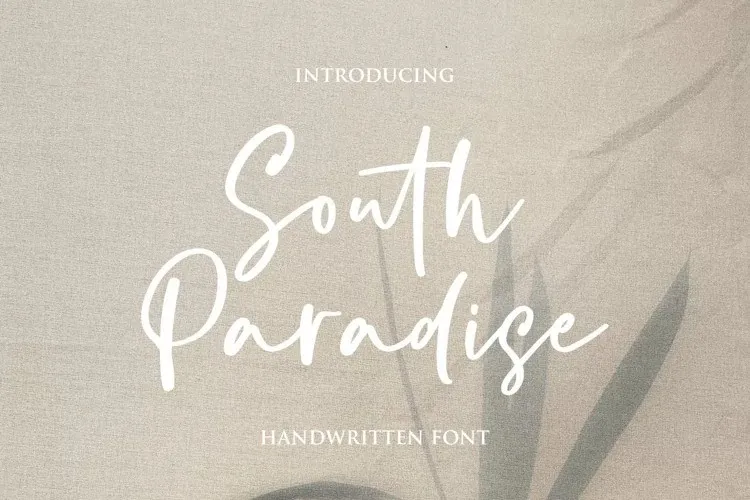
South Paradise Font – Download Grátis
A South Paradise Font é uma elegante fonte script que captura os melhores traços do modernismo, com um estilo marcante feito especialmente para quem busca uma solução perfeita para várias necessidades de design. Feita pelo designer fikryal no formato de fontes moderna e casual, ela se destaca pela sua capacidade versátil e adequada para diversos tipos de projetos gráficos. Este fonte é ideal para criações visuais como logomarcas, identidades de marca, títulos, posts nas redes sociais, anúncios, embalagens de produtos, designs dos produtos, etiquetas, fotografias, marcadores de água, eventos especiais, revistas e design web. A South Paradise Font é uma escolha perfeita para designers buscando manter um equilíbrio elegante entre a simplicidade do modernismo e a personalidade única da fonte.